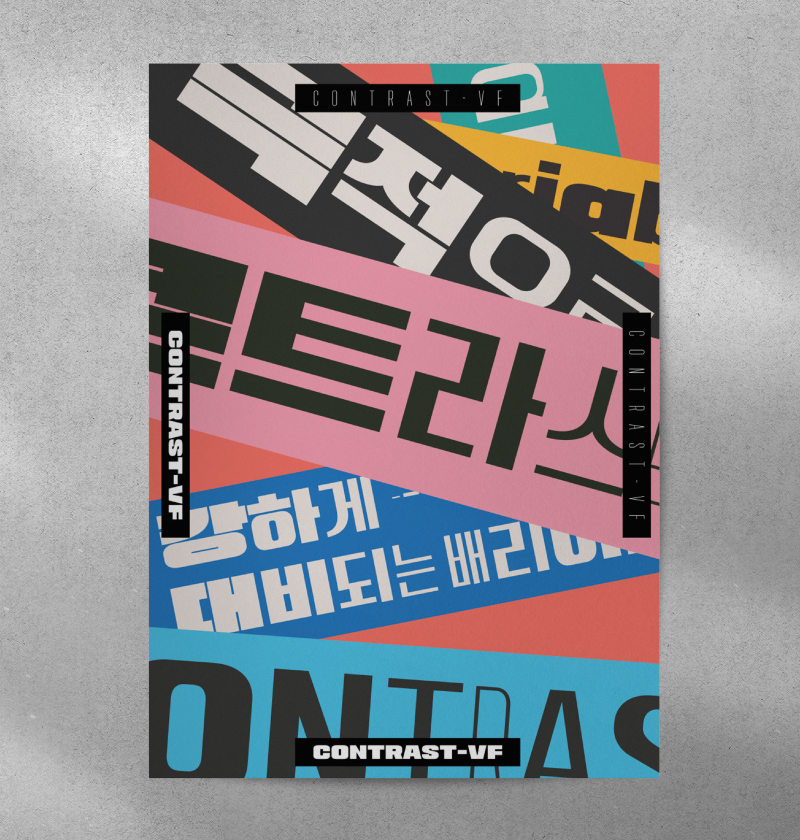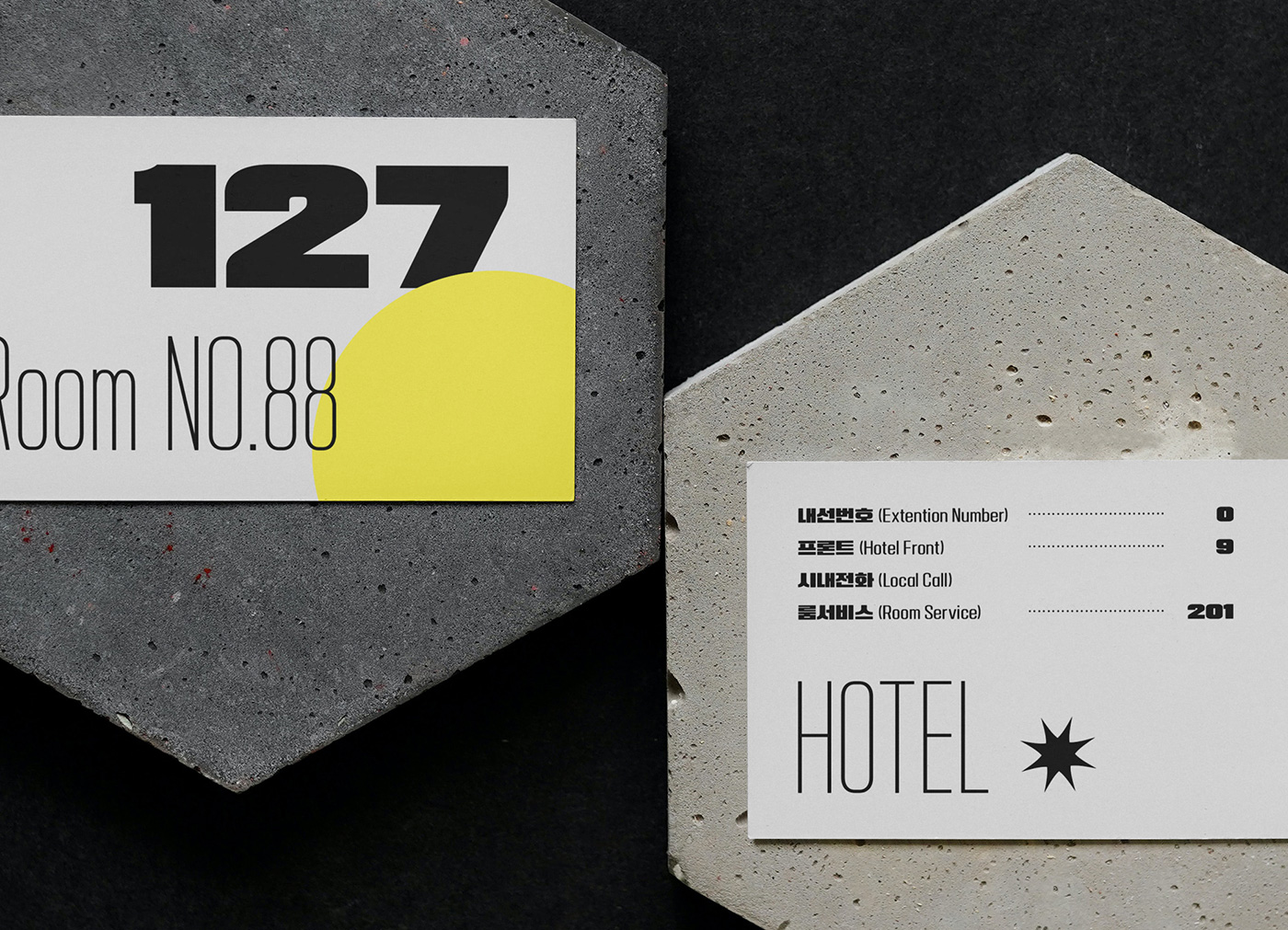
2개의 시리즈로 구성된 Rix콘트라스트 배리어블 폰트의 오픈타입 적용 버전입니다.
Day 축을 통해 글자의 굵기와 폭이 순차적으로 다르게 나타나는 효과를 조절할 수 있습니다.
한 글줄 내에서 글자들이 좌우로 확장되거나 축소되면서 강렬하고도 재미있는 인상을 줍니다.
2개의 시리즈로 구성된 Rix콘트라스트 배리어블 폰트의 오픈타입 적용 버전입니다.
Day 축을 통해 글자의 굵기와 폭이 순차적으로 다르게 나타나는 효과를 조절할 수 있습니다.
한 글줄 내에서 글자들이 좌우로 확장되거나 축소되면서 강렬하고도 재미있는 인상을 줍니다.